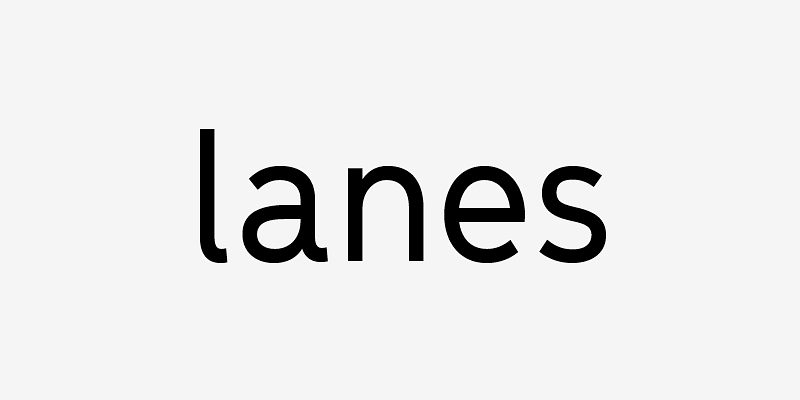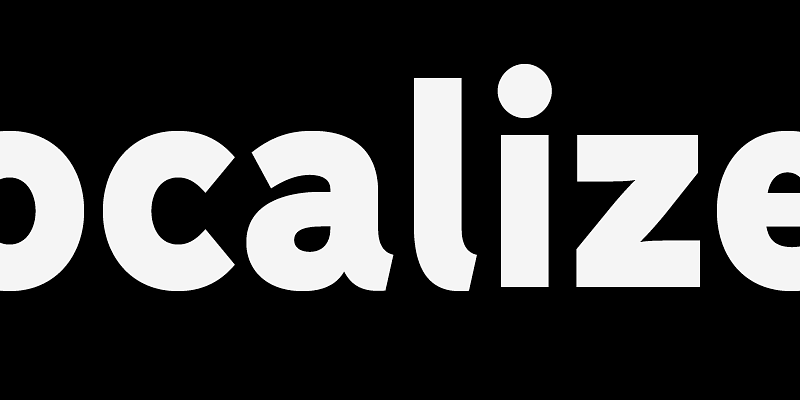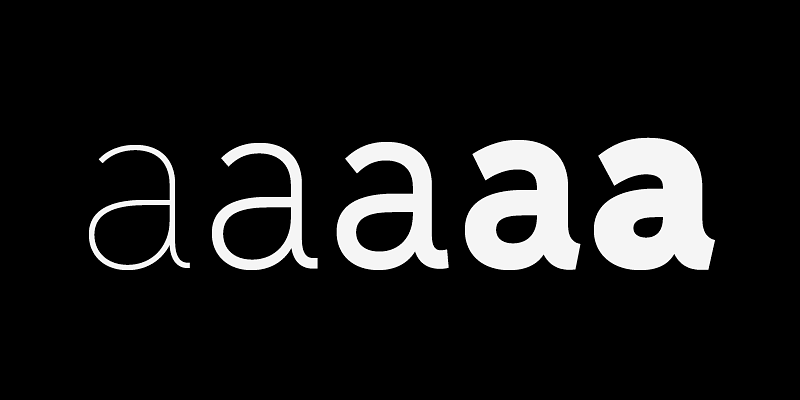
„Menca“ orientiert sich an den funktionalen Schriftformen aus dem Ingenieurwesen, wie sie auf Verkehrsschildern, Industrieschildern und technischen Markierungen zu finden sind. Die Schriftfamilie umfasst fünf Schriftstärken von „Thin“ bis „Black“, jeweils mit passender Kursivschrift, und unterstützt den erweiterten lateinischen Schriftsatz. Die Menca bietet erweiterte typografische Merkmale wie unterschiedliche Formvarianten für Versalien und Minuskeln, Brüche, hoch- und tiefgestellte Zeichen, stilistische Alternativen sowie nichtproportionale und proportionale Versalziffern.